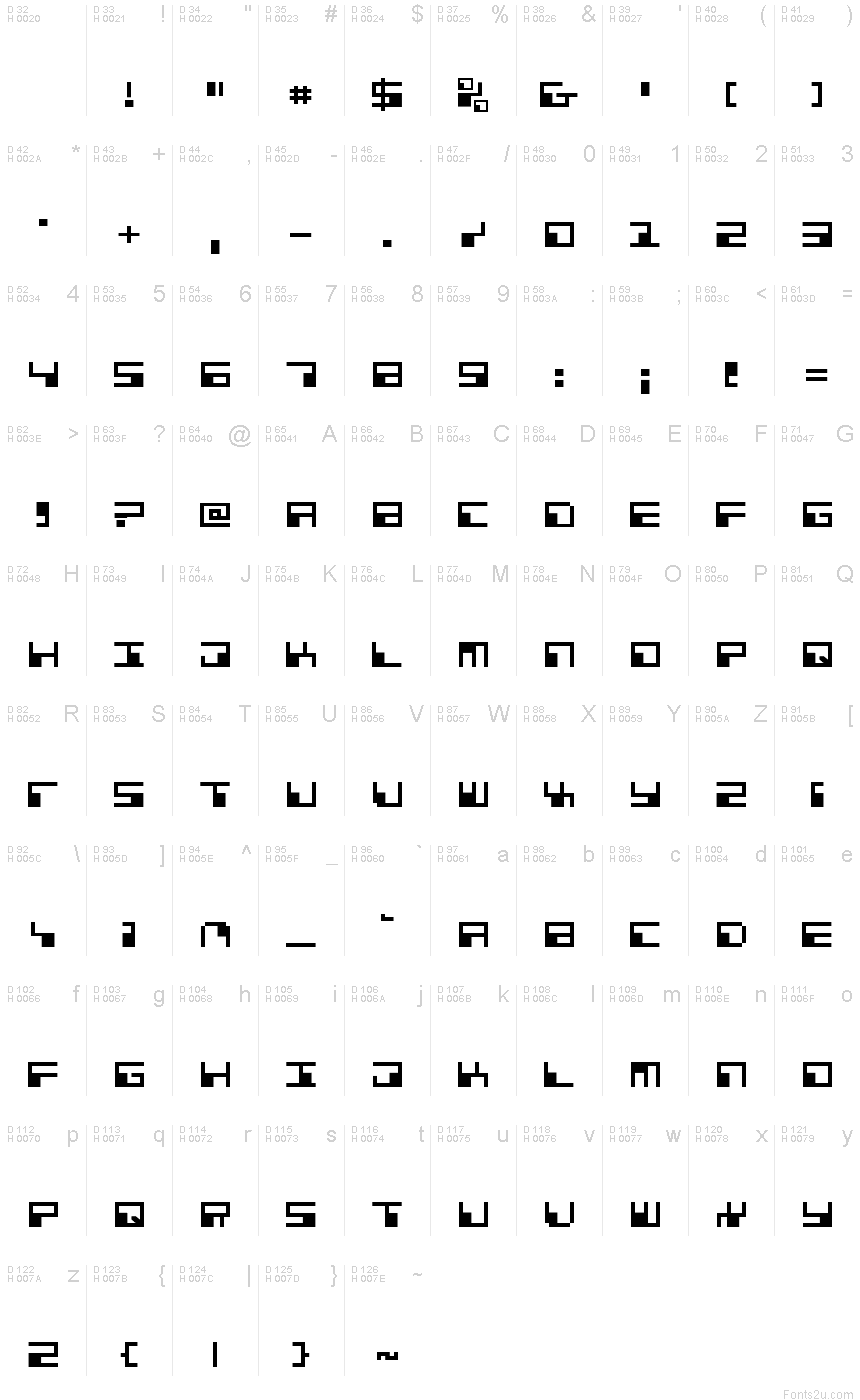
Phaser Bank Expanded od Iconian Fonts to darmowy technokrój typu display o surowym, modułowym rytmie i wyraźnym klimacie arcade sci-fi. Wielkie litery zbudowano z grubych kątów prostych i otwartych prostokątnych prześwitów, dzięki czemu znaki sprawiają wrażenie zaprojektowanych inżynieryjnie, a nie narysowanych. Ich szeroka postawa nadaje nagłówkom jednostajny, maszynowy puls.
Krój ten naturalnie odnajdzie się w logo gier, ulotkach muzyki elektronicznej, tytułach na plakatach i futurystycznych znakach marki, gdzie krótkie słowa wymagają wyrazistego, cyfrowego sznytu. Jako darmowy font, sprawdzi się również w tekstach na okładkach i monogramach, zwłaszcza gdy chcesz, aby litery wyglądały jak część panelu sterowania lub interfejsu w starym, kosmicznym stylu.
Phaser Bank Expanded